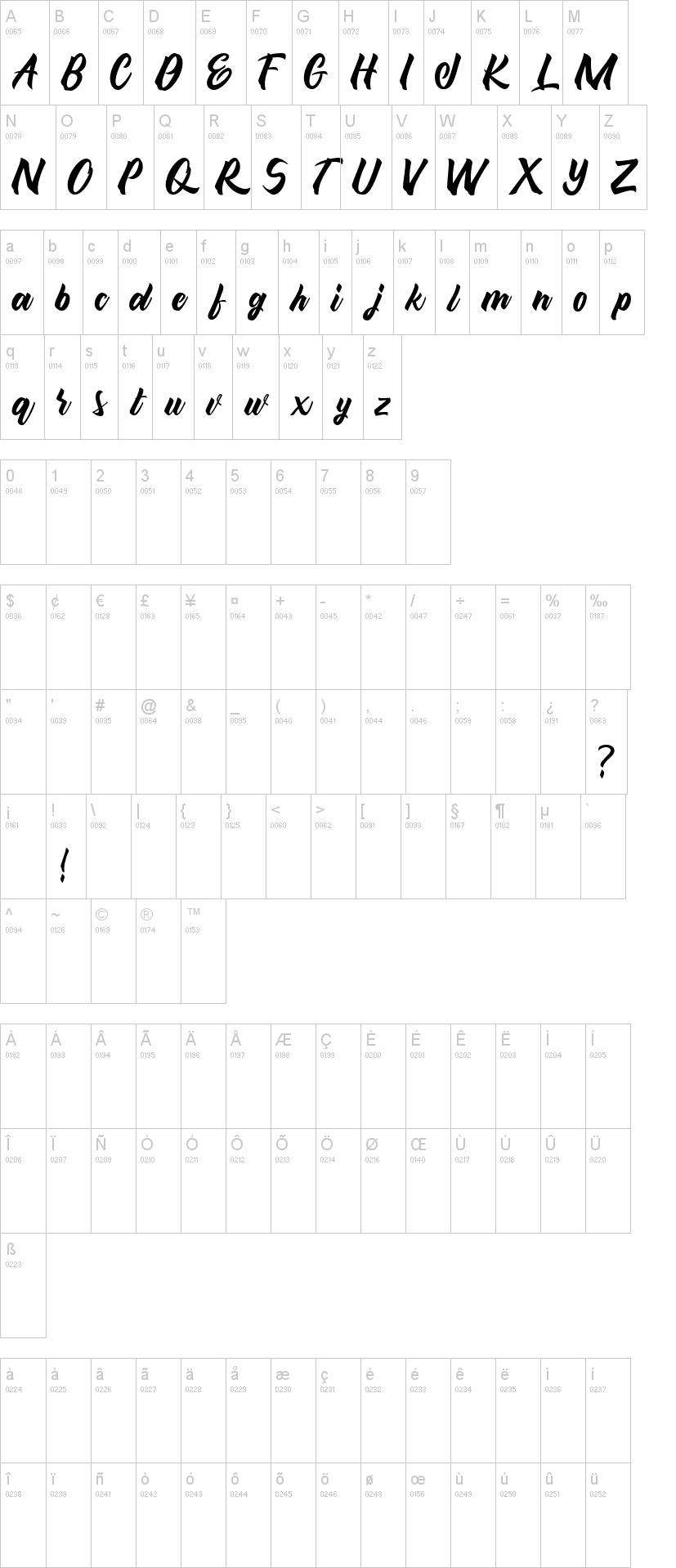
Maghody
Maghody 是一款漂亮的手写字体,具有个性化和艺术感。它的字母形状类似于手写的草书风格,但是字母之间的间距很合理,可以保证易读性。这款字体适合用于设计海报、广告、卡片、标志等需要具有艺术感的场合。Maghody 字体包括大写字母、小写字母、标点符号和数字,支持多种语言的字符。这款字体可在多种平面设计软件中使用,如 Photoshop、Illustrator、InDesign 等。
Maghody是一款非常不错的手写艺术字体,具有很好的视觉感,适合于文化类的宣传设计、商业类品牌的广告和产品包装设计以及个性化文字排版等较多场景。